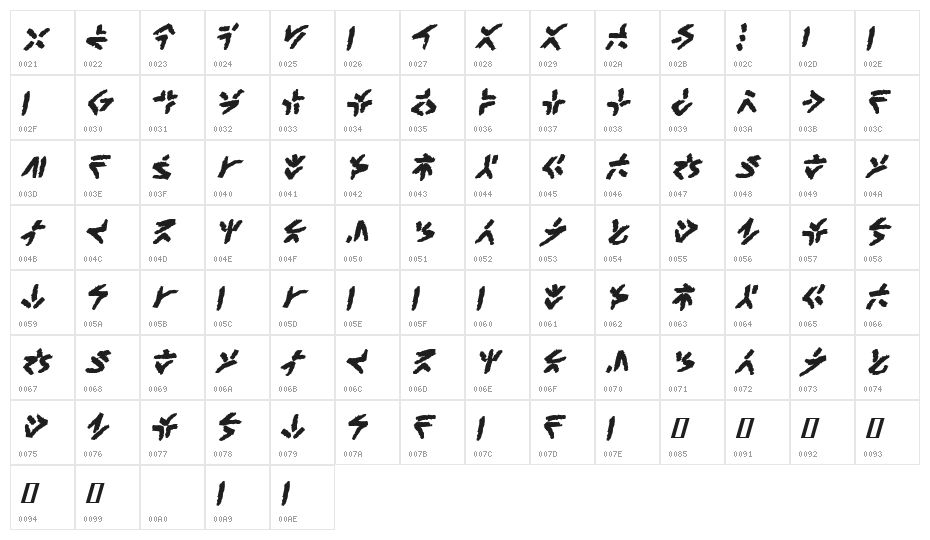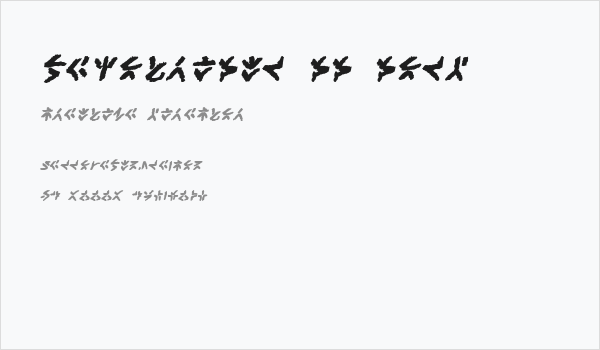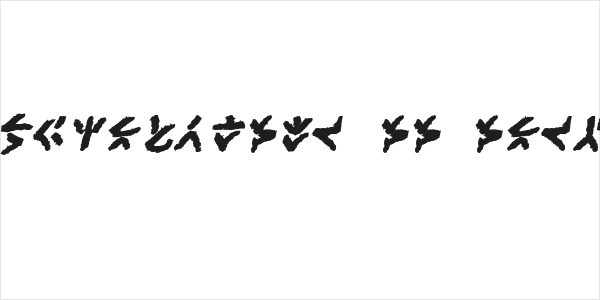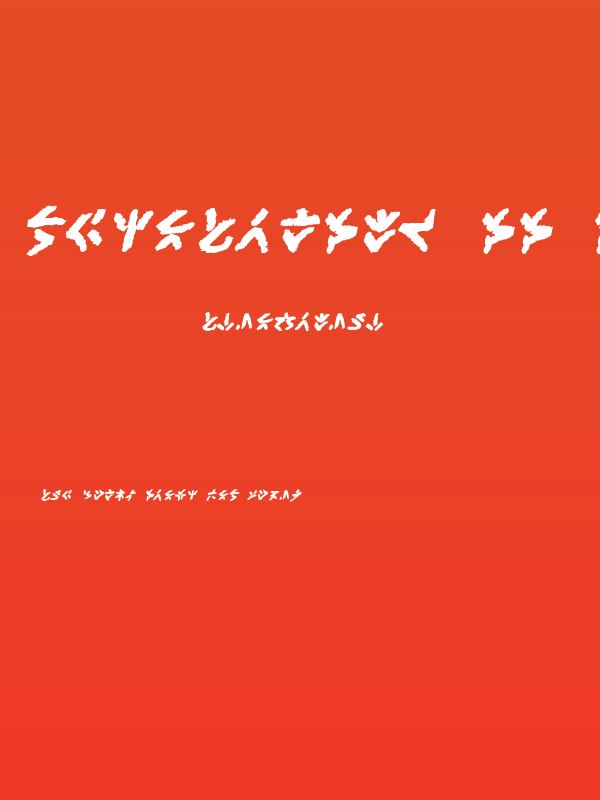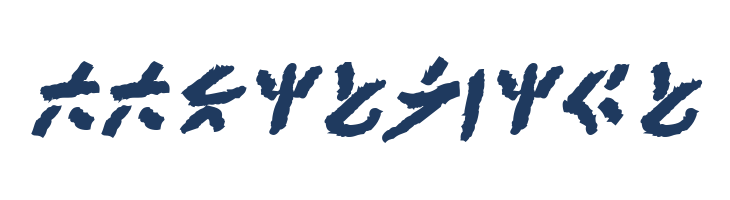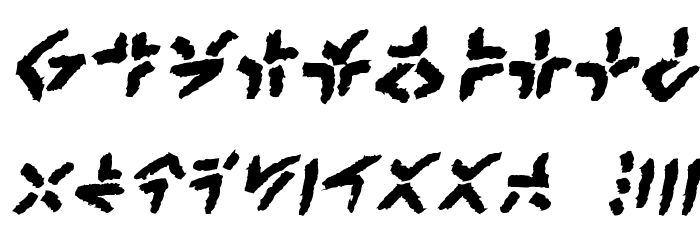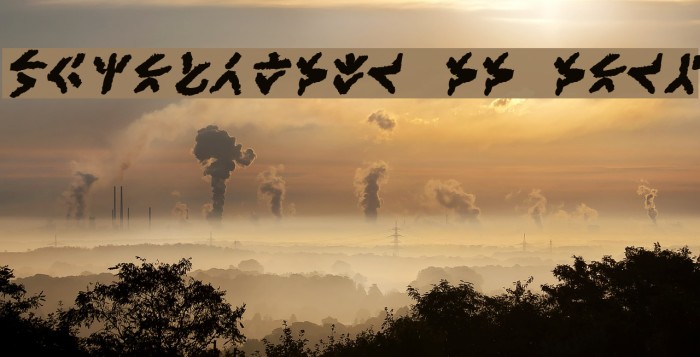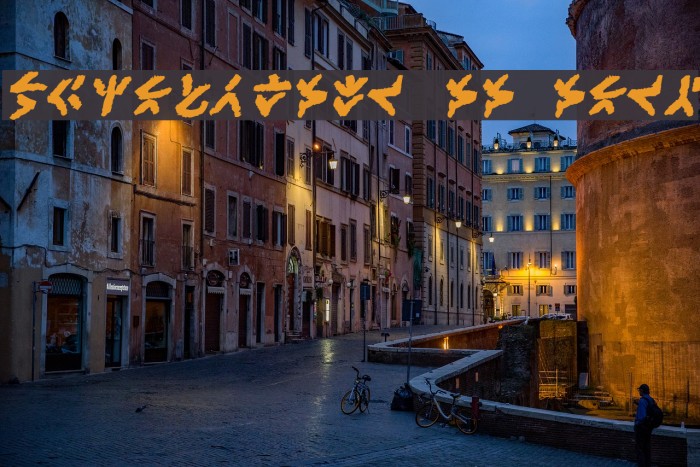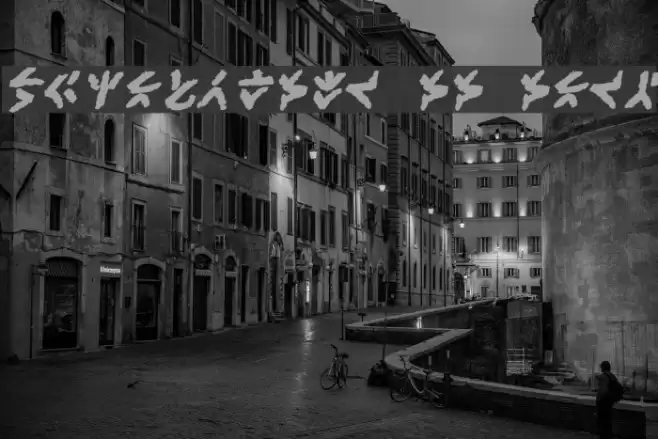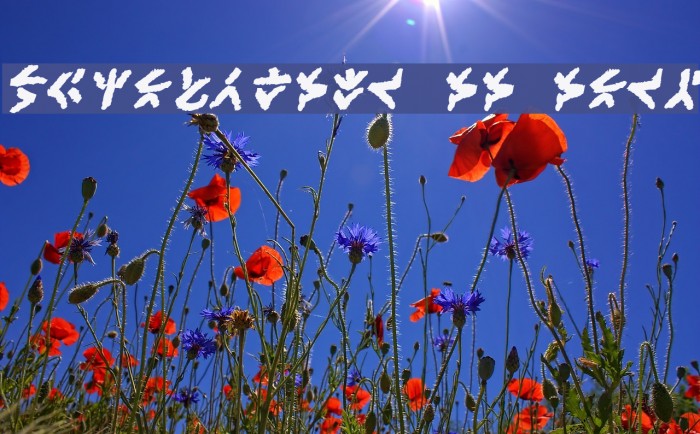
XenoTribal BB Bold Font
| Cas d'utilisation | Logos, Posters, Branding |
| Projets proposés | Ideal for use in logos, posters, and branding projects that aim to convey strength and cultural depth. |